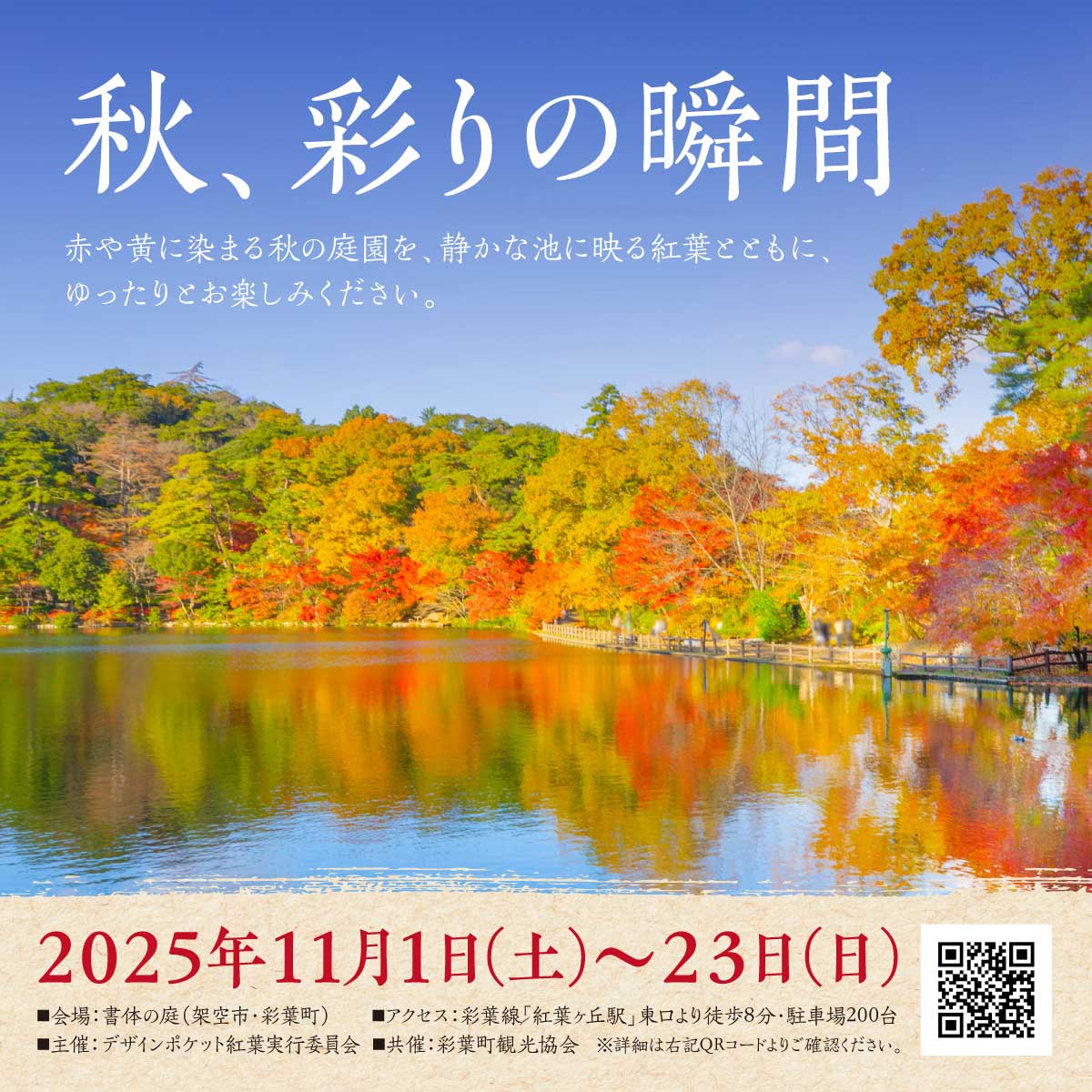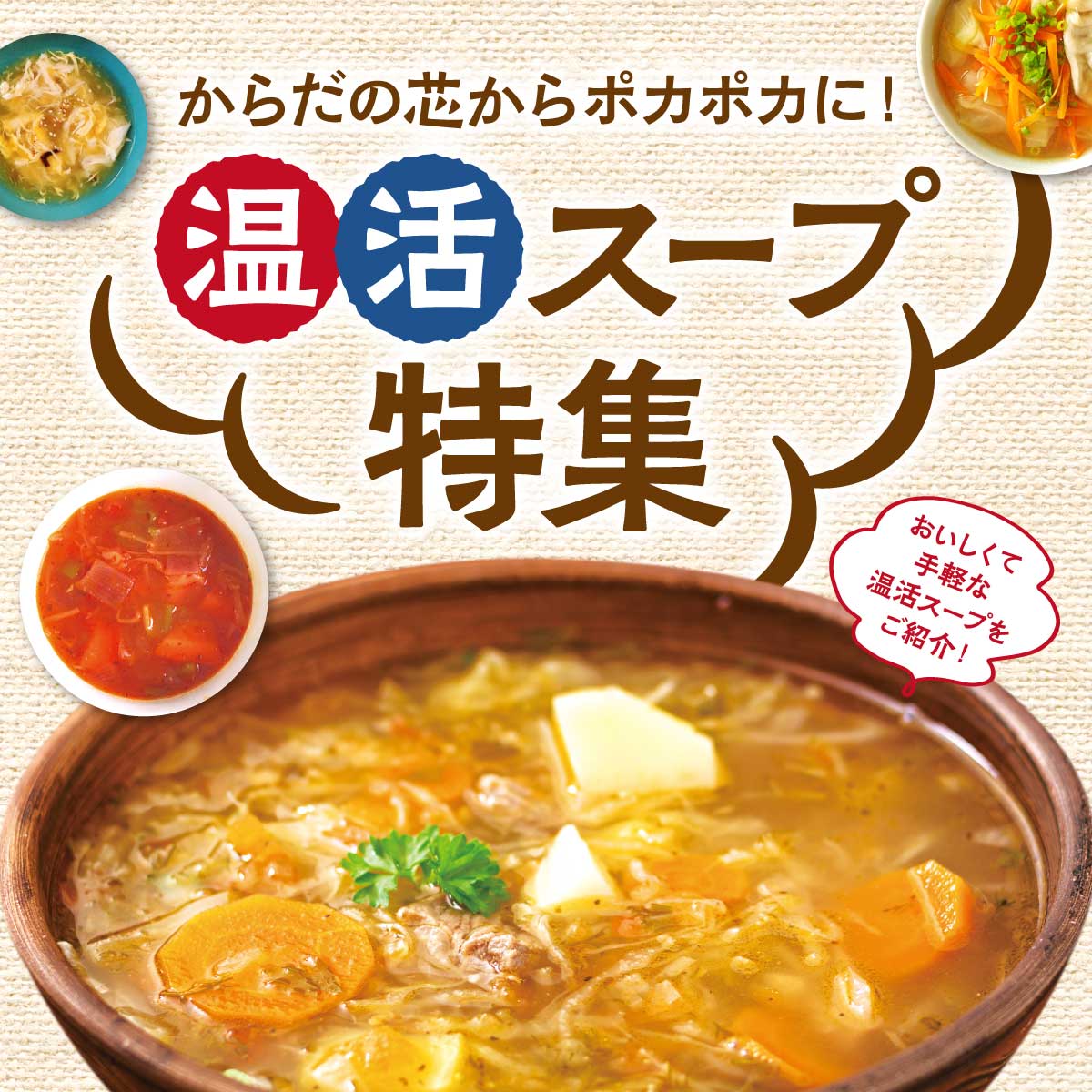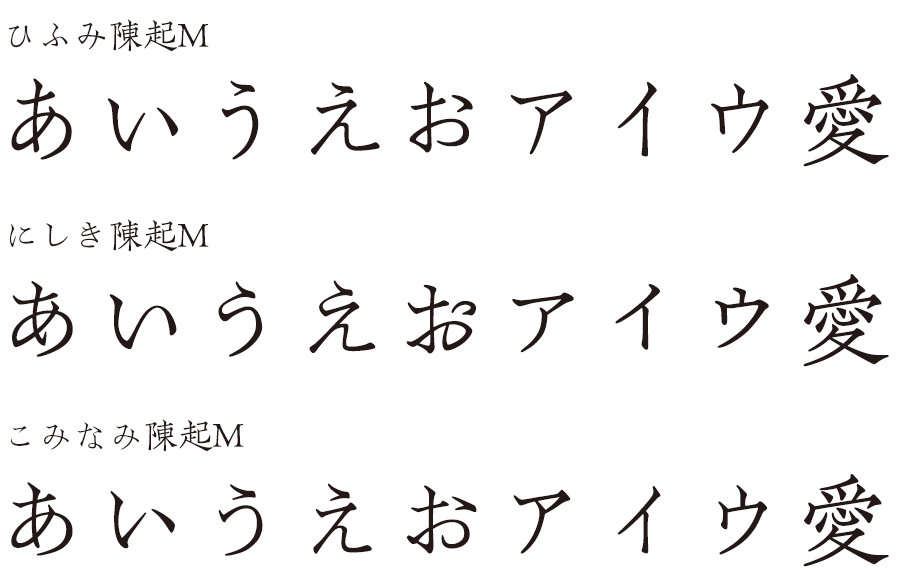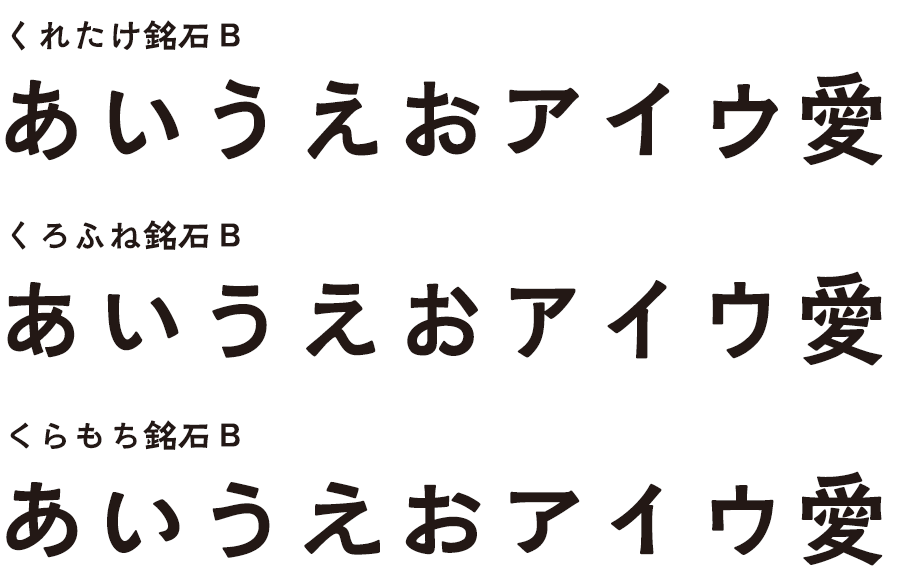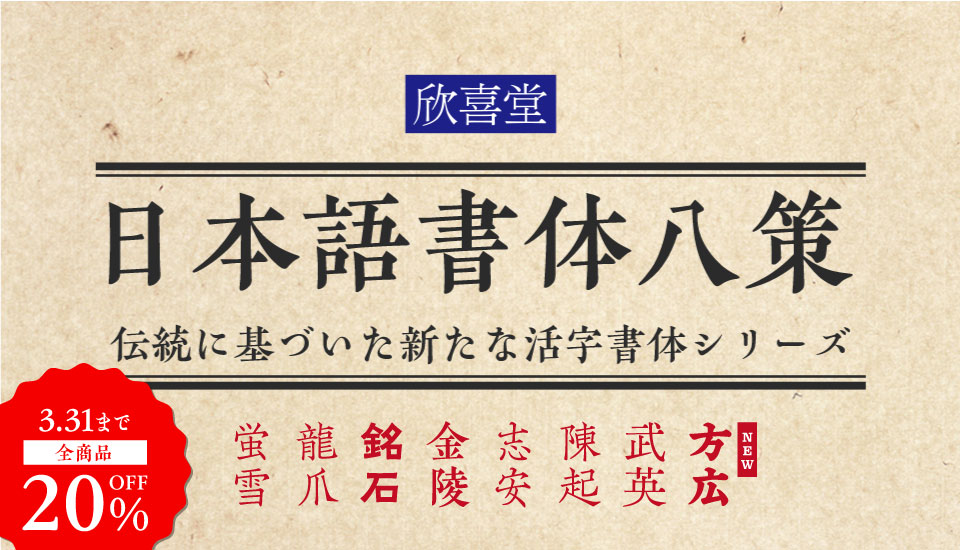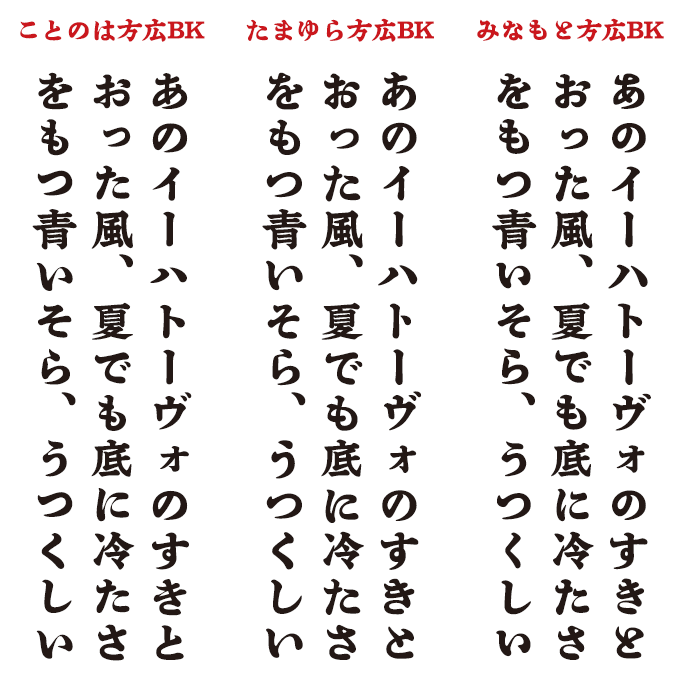
欣喜堂の日本語書体八策 - 伝統に基づいた新たな活字書体
「欣喜堂」の核となる日本語書体八策シリーズでは、日本と中国、欧米の古い書物などから復刻した和字書体(かなとカナ)と漢字書体、欧字書体を組み合わせ、伝統に基づいた新たな活字書体を制作しています。
日本語書体八策シリーズ (漢字+和字 総合書体)
欣喜堂 臨安宋朝体 陳起(りんあんそうちょうたい ちんき)
「中世安竹体 方広」は、北宋代の仏教経典『大方廣佛華巖経』(龍興寺、990–994)に用いられた字様をもとに翻刻した中世安竹体「方広」、ロバート・ベズリによる「クラレンドン」が掲載されている『印刷活字総合見本帳』(ファン・ストリート活字鋳造所、1857年)所収の見本から復刻したスラブセリフ体「K.E.Pisces」を組み合わせた日本語書体です。
BK (Black) ウェイト
M (Medium) ウェイト
欣喜堂 過渡期明朝体 武英(かときみんちょうたい ぶえい)
この漢字書体「武英」は中国の清・康熙帝が計画した銅活字版『古今図書集成』から復刻したものです。
『古今図書集成』は、中国・清朝の康熙帝が、陳夢雷等に命じて編纂を開始したものです。清の康煕帝・雍正帝・乾隆帝の時代に、武英殿および民間出版社によって銅活字や木活字で刊行された書物にあらわれている書体は、明代の刊本字様である「明朝体」と、清代後期の「近代明朝体」との過渡期にあたるので、そのカテゴリーを「過渡期明朝体」としています。
欣喜堂 臨安宋朝体 陳起(りんあんそうちょうたい ちんき)
原資料は『南宋羣賢小集』(1208年-1264年、陳宅書籍鋪)です。
中国・南宋の首都であった「臨安〔りんあん〕」とは、金の圧迫で南方に移った宋が、1129年に臨時の都の意味で名づけたもので、現在の杭州市にあたります。宋朝の国力の衰えた時期にも、臨安の街ではまだ活発な商業活動が行われていました。臨安では、ますます書物の復興や印刷の隆盛をみました。とりわけ唐から北宋にかけての名家による詩文集や文学書の刊行が中心になりました。
南宋の首都であった臨安城中の棚北大街には多くの書坊が建ち並んでいたといわれますが、そのなかでも陳宅書籍鋪が刊行した書物は注目をあびました。これを「臨安書棚本」と呼んでいます。陳宅書籍鋪では、整然として硬質な字様を完成させましたが、この字様によって書写から独立した「工芸の文字」が誕生することになりました。
M (Medium) ウェイト
B (Bold) ウェイト
欣喜堂 福建元朝体 志安(ふっけんげんちょうたい しあん)
「元朝体」は中国「元」の時代に書物の規制が厳しくなる中、福建地方の民間出版社から作りだされた書体と言われています。この時代の有名な出版社では余志安の「勤有書堂」があり、この勤有書堂の持つ字様が元時代の福建刊本の特徴がよくあらわれている典型的な書体です。なかでも李白の作品集の現存する最も古い注釈書『分類補註李太白詩』(1310年)の書風は、元時代の福建刊本の特徴がよくあらわれている元朝体で、漢字書体「志安」のベースとなっています。
伝統と歴史を感じさせる漢字書体「志安」に、仮名書体「げんろく」「ばてれん」「ひさなが」を組み合わせた3種類を販売中です。
欣喜堂 KOげんろく志安M、KOばてれん志安M、KOひさなが志安M
福建元朝体 志安M Combination 3
元朝体「志安M」に3種類の和字を従属させた3書体(KOげんろく志安M、KOばてれん志安M、KOひさなが志安M)のセットです。
KOげんろく志安M、KOばてれん志安M、KOひさなが志安M
「福建元朝体 志安M Combination 3」に収録の各書体の単品です。
欣喜堂 正調明朝体 金陵 (せいちょうみんちょうたい きんりょう)
この書体は中国の明王朝時代「国子監」より刊行された木版刊本、『南斉書』にみられる端正な明朝体字様を現代に再生したものです。国子監とはもともとは隋王朝のころに設立された大学のことで、明王朝ではすべての学問を統括する中央官庁となりました。王朝によるもっとも典型的な官刊本のひとつが『南斉書』で、由緒正しい明朝体字様がうかがえる書物です。「正調明朝体 金陵」では明朝体の端正な字様に加えて、原型の木版が持つあたたかみを合わせて復刻しています。
漢字書体の「金陵」に、仮名書体「あおい」「きざはし」「さおとめ」を組み合わせた3種類があり、それぞれ Medium・Bold の2ウエイトが販売中です。
M (Medium) ウェイト
欣喜堂 KOあおい金陵M、KOきざはし金陵M、KOさおとめ金陵M
正調明朝体 金陵M Combination 3
明朝体「金陵M」に3種類の和字を従属させた3書体(KOあおい金陵M、KOきざはし金陵M、KOさおとめ金陵M)のセットです。
KOあおい金陵M、KOきざはし金陵M、KOさおとめ金陵M
「正調明朝体 金陵M Combination 3」に収録の各書体の単品です。
B (Bold) ウェイト
欣喜堂 KOあおい金陵B、KOきざはし金陵B、KOさおとめ金陵B
正調明朝体 金陵B Combination 3
明朝体「金陵B」に3種類の和字を従属させた3書体(KOあおい金陵B、KOきざはし金陵B、KOさおとめ金陵B)のセットです。
和字書体シリーズ
欣喜堂 和字書体シリーズ
日本と中国の古い書物などから復刻した和字(ひらがな・カタカナ) 書体「KOシリーズ」のほか、あたらしいスタンダードの構築をめざすカジュアルな和字書体「SDシリーズ」も揃っています。
「欣喜堂」の使用例
チラシ
使用書体:きざはし金陵・まどか蛍雪
サンプルその1
SNS投稿・Webバナー
使用書体:くれたけ銘石
サンプルその1